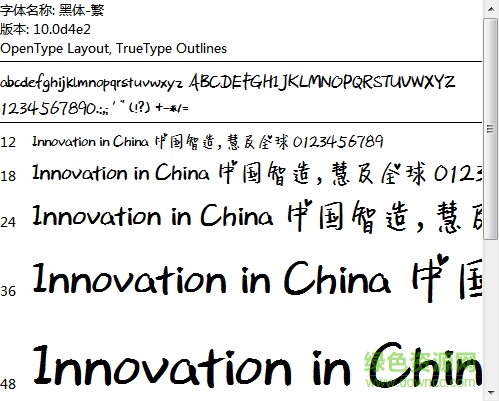
凉茶字体是一款十分出彩的艺术手写字体,有着十分流畅细腻的笔触,干净简洁的结构,更有可爱的心型点缀让你的文字更加生动,很有毛笔书法字体的风格特色,喜欢的朋友就来绿色资源网下载收藏吧!
凉茶字体带有小清新的爱心设计让其在广告设计、网页设计、包装设计等领域均有着不错的视觉效果,是一款非常清秀美观的字体!
凉茶字体完整不缺字,能满足广大设计师们的日常生活需要,支持繁简体输入,有着十分独特的艺术效果,相信你一定会喜欢!